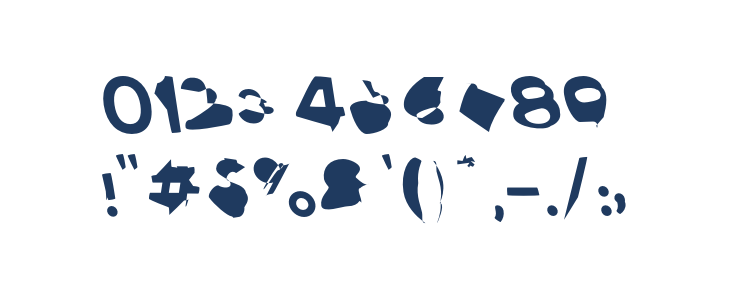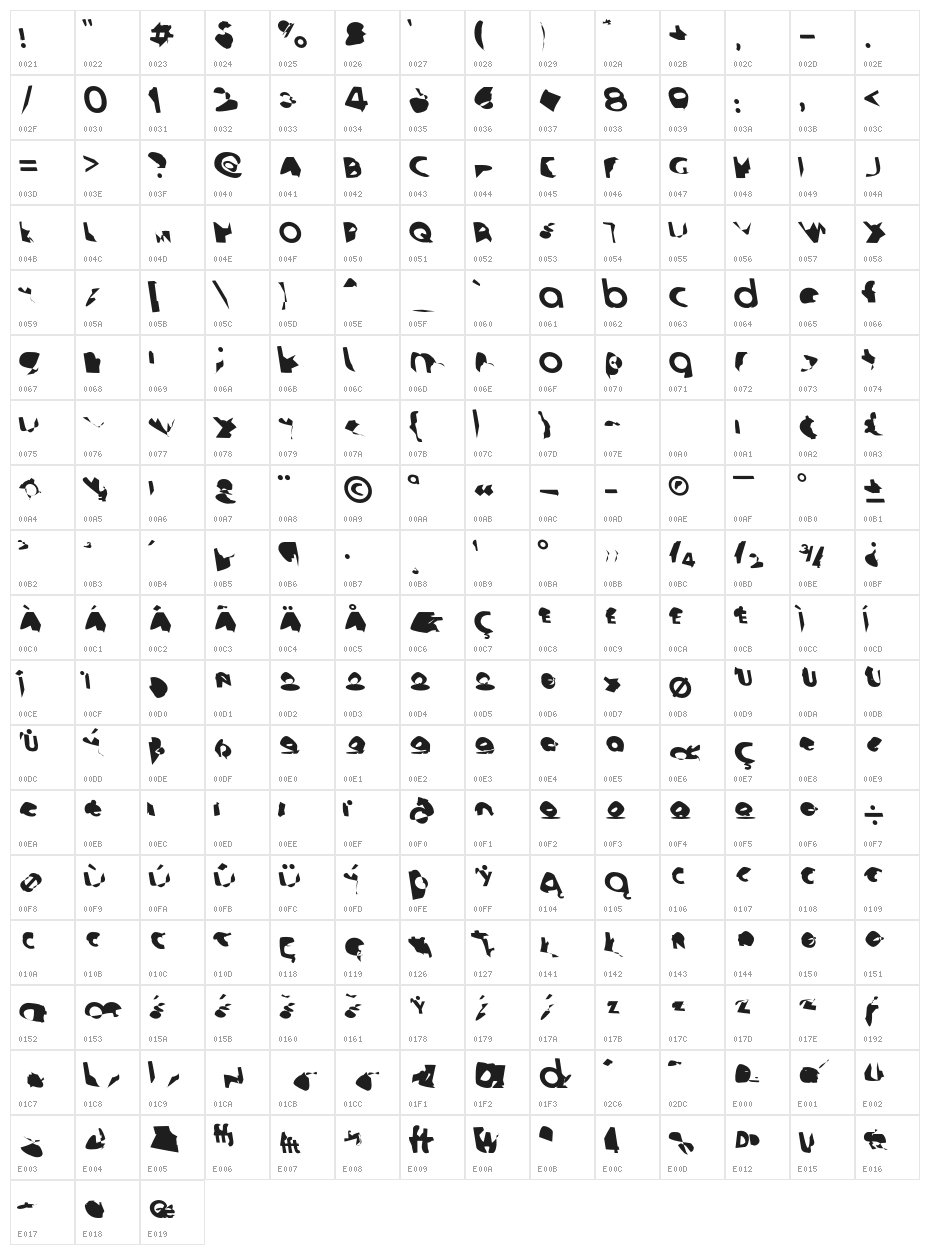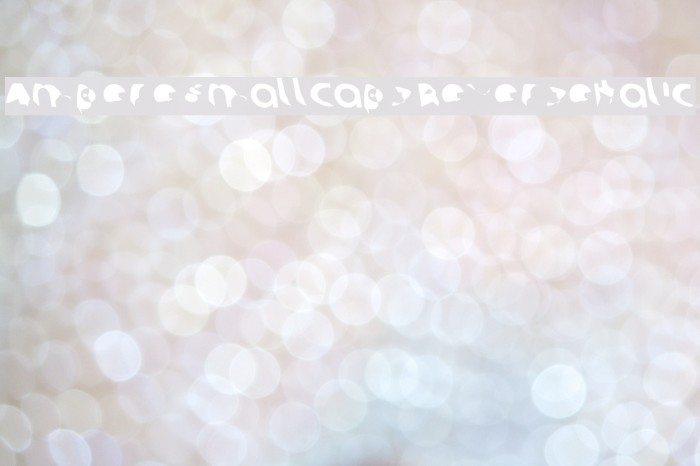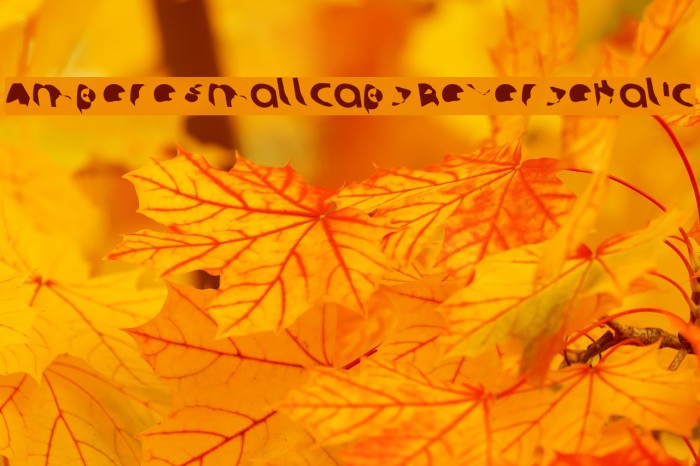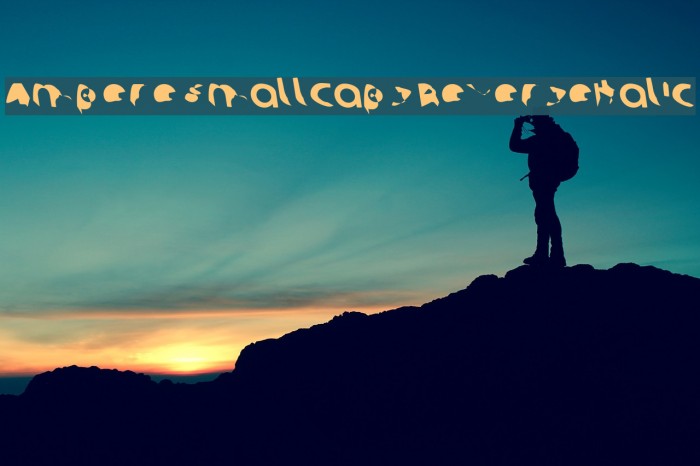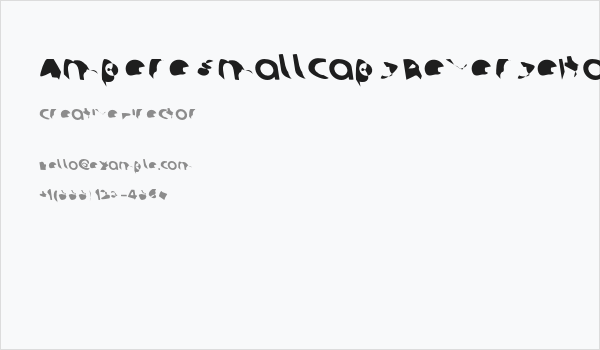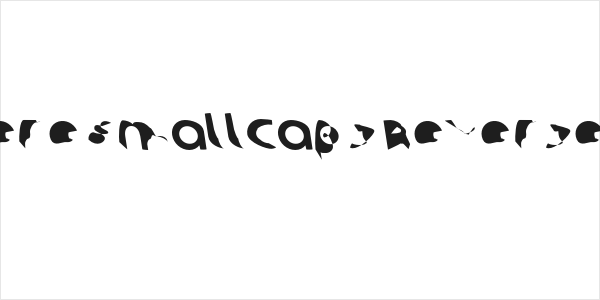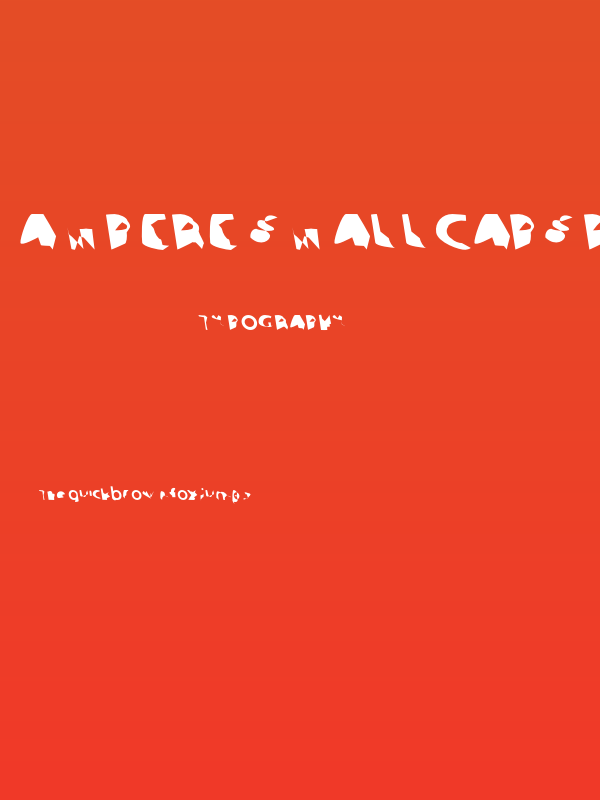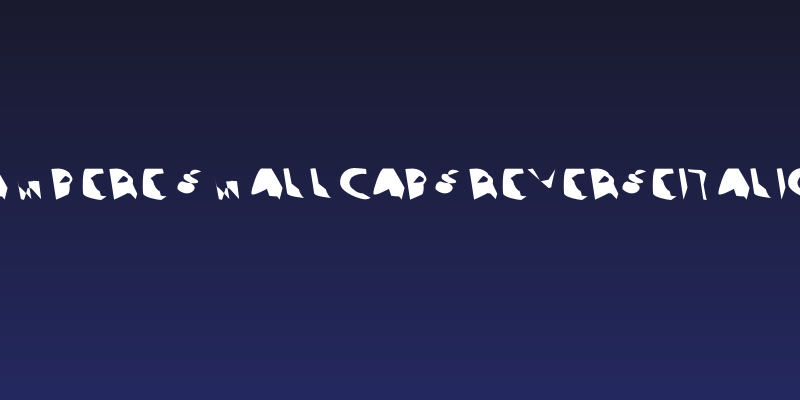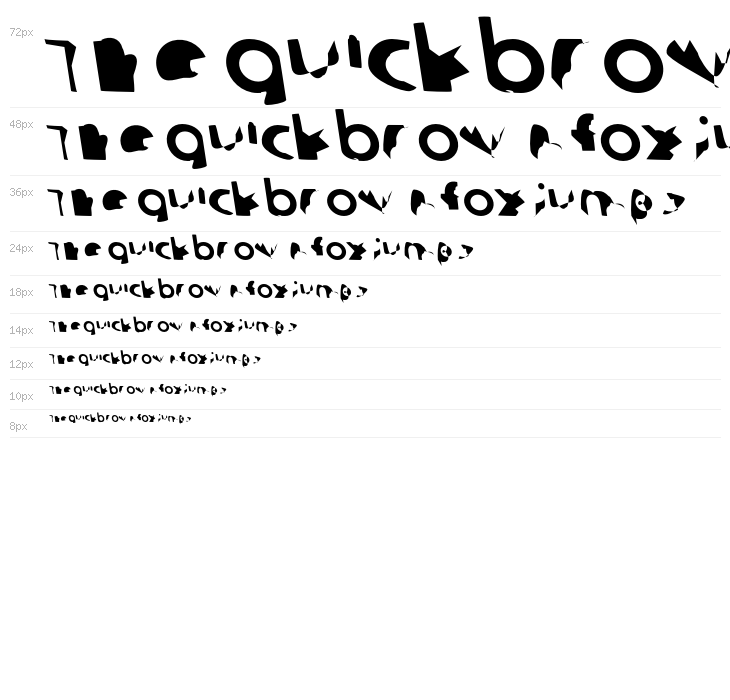
Ampere SmallCaps ReverseItalic Font
| Vorgeschlagene Projekte | Ideal for avant-garde posters, album covers, or any project seeking a modern, edgy aesthetic. |